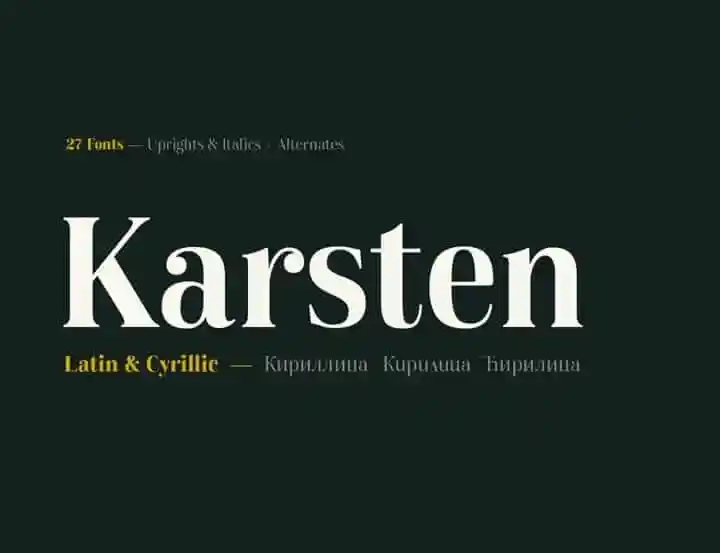
A Karsten Serif Font é uma nova serif typeface elegante inspirada nos sinais encontrados nas antigas construções holandesas em Java. Desenvolvida por Nasir Udin, essa fonte transmite um estilo moderno ao mesclar elementos de duas culturas: o oriente e o ocidente. Ela é uma síntese das contribuições do arquiteto holandês Herman Thomas Karsten para a arquitetura e urbanismo na Indonésia. A fonte honra seu designador, um profundo conhecedor da arquitetura moderna, trazendo consigo uma beleza que se integra perfeitamente tanto no design de novos projetos quanto nas antigas construções indonesianas. Inspirada na simplicidade e elegância dos sinais tradicionais, a Karsten Serif é ideal para designers buscando uma fonte moderna que preserva um toque de elegância clássica.